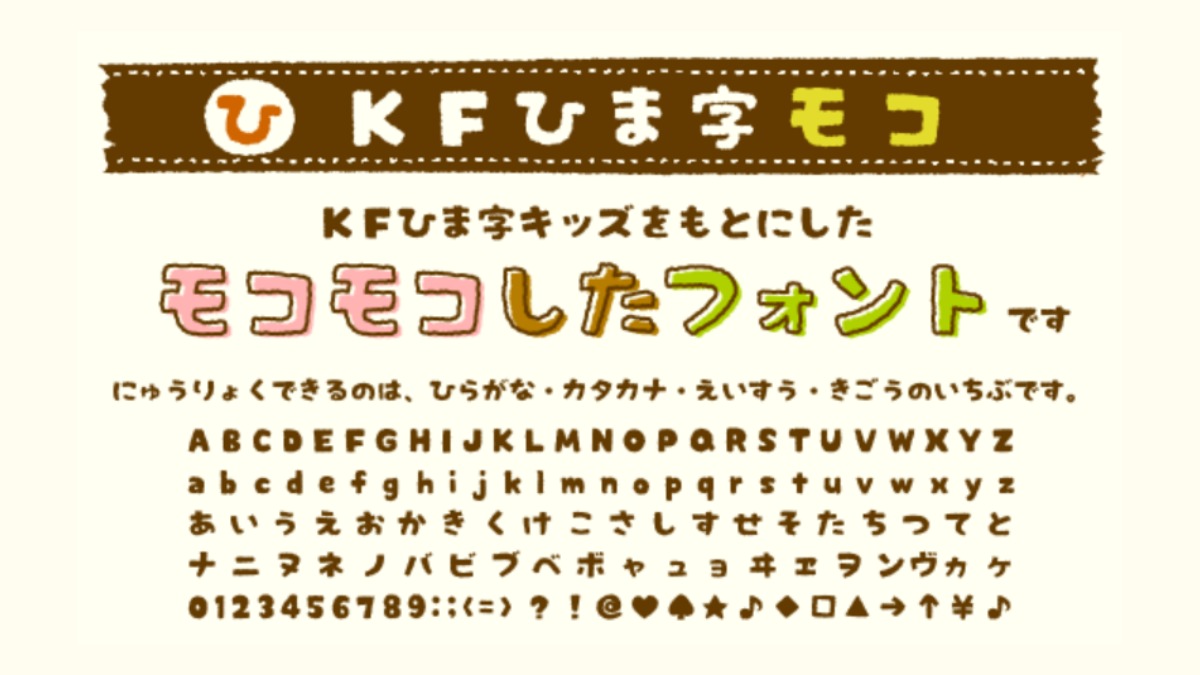
KFひま字モコは、KFひま字キッズ文字を元にした、輪郭がモコモコ(ガタガタ?)としたかわいらしい日本語フリーフォントです。太めの文字なので見出しやタイトルに向いているフォントです。
KFひま字モコの詳細情報
| 書体名 | KFひま字モコ |
| 書体 | デザイン書体 |
| 収録文字 | アルファベット カタカナ ひらがな 数字 記号 |
KFひま字モコは、KFひま字キッズ文字を元にした、輪郭がモコモコ(ガタガタ?)としたかわいらしい日本語フリーフォントです。太めの文字なので見出しやタイトルに向いているフォントです。